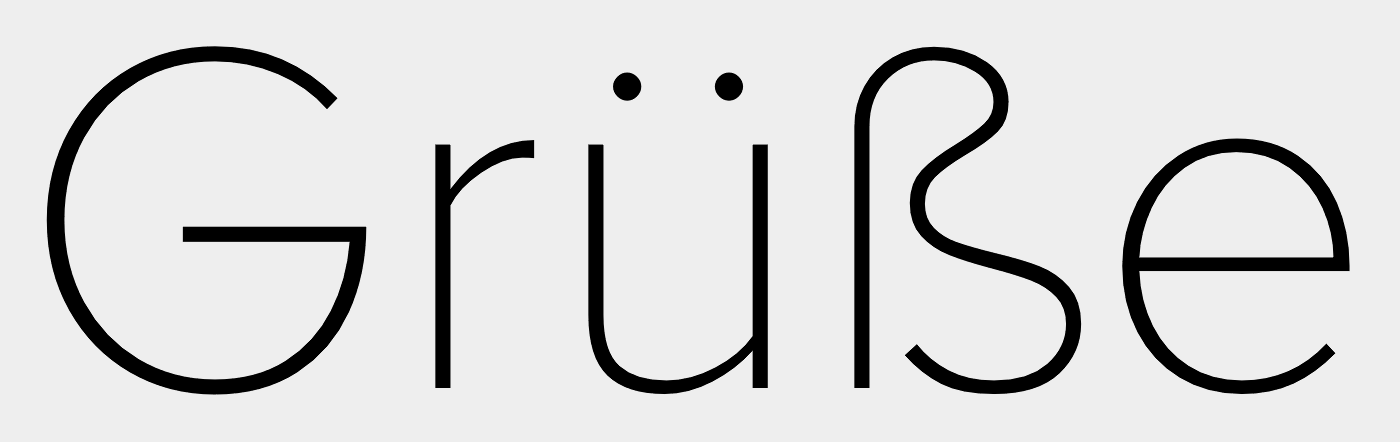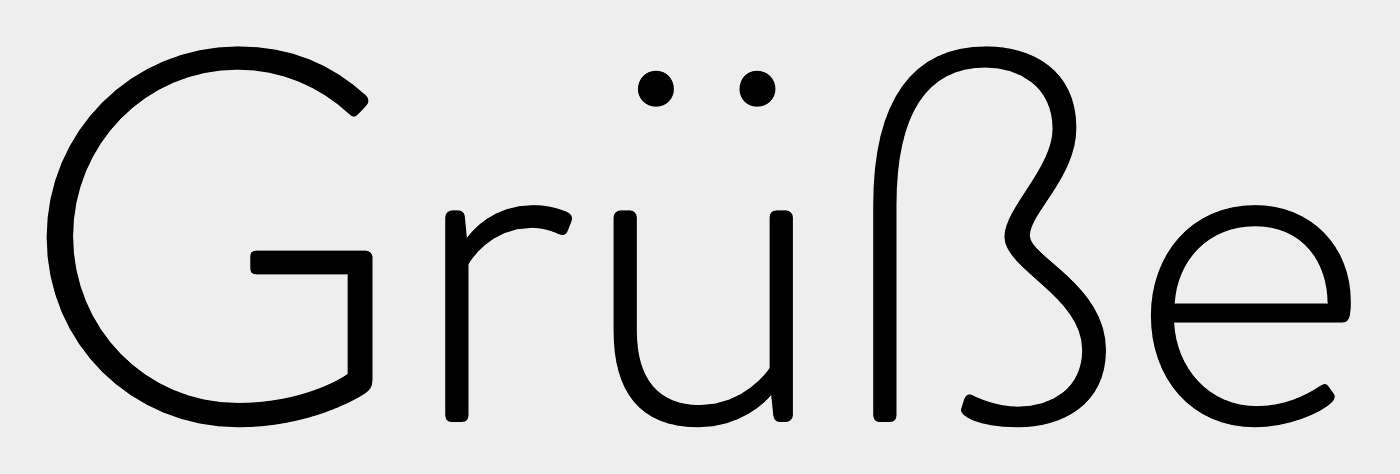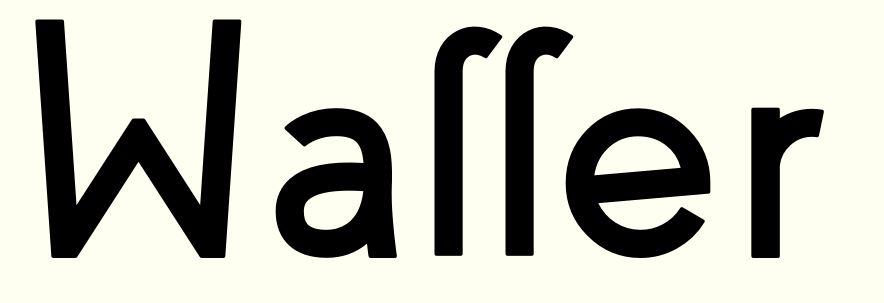
ß bei Schrift Coves
Wir gestalten Einladungskarten mit der Schrift Coves, die wir bei dafont bzw. befonts heruntergeladen haben.
Leider gibt es kein "ß" in dieser Schrift.
Hättet ihr mir einen Tipp, wie ich hier weiterkomme bzw. kennt ihr evtl. einen "erweiterten Schriftsatz" (wenn man das so nennen kann), bei dem das "ß" in der Schrift integriert ist?
Oder wißt ihr evtl. eine Schriftart, die der Coves nahe kommt und das "ß" keine Unterschied macht?
Ich wäre euch für eure Hilfe echt dankbar, da >anschliessend< oder >Grüsse< ohne "ß" einfach doof aussehen.
Wir gestalten Einladungskarten
Was ähnliche Schriften angeht, sag mal, was an der Coves es dir besonders angetan hat. Geometrische serifenlose Schmuckschriften gibt es nun wahrlich wie Sand am Meer. Und wenn es unbedingt kostenlose Schriften sein müssen, kuck lieber hier; diese Schriften dürfen auch kommerziell benutzt werden.
Oder wißt ihr evtl. eine Schriftart, die der Coves nahe kommt und das "ß" keine Unterschied macht?
Du willst das ß einer anderen Schrift mit Zeichen der Coves mischen? Vergiss das mal besser. Du könntest catfonts fragen, ob er dir ein passendes ß macht und wie viel Geld er dafür haben will.
Du hast nicht zufällig schonmal die Nachbarin mit deiner Mutter verwechselt?
Ja, das wäre der sinnvollere erste Schritt. Wobei die Wahrscheinlichkeit, dass du schneller als der Designer der Coves bist, recht groß ist.
Ich wäre euch für eure Hilfe echt dankbar, da >anschliessend< oder >Grüsse< ohne "ß" einfach doof aussehen.
Sag einfach, du hast die Karten exklusiv aus der Schweiz importiert :hammer:
Bei fontsquirrel sind doch ein paar Schriften, die als Ersatz passen, wenn dir das zu lange dauert, bis der Designer nachbessert. Warum gerade das ß fehlt verstehe ich auch nicht, sonst ist ja einiges dabei :-?
Vielen Dank für eure Tipps! Ich hab mal geschaut, von den Schriftvorschlägen lässt sich evtl. was verwenden....
Allerdings wärs halt schon ne runde Sache, wenn es das "ß" in der Schrift gäbe - ich habe es auch schon bei einem kommerziellen Papeteriehersteller gesehen:
Als Bild einfügen habe ich schon probiert, aber das ist auch icht das Gelbe vom Ei....
Ich bräuchte das "ß" halt demnächst... Ich frage auf ejden Fall mal bei dem Schriftdesigner Jack Harvatt an.
Es wäre aber wirklich toll, wenn catfonts mir helfen könnte!?!
Ich würde die Schrift wegpacken, wenn sie kein ß hat und komplett eine andere nehmen. Vielleicht bessert er irgendwann nach, dann kann man nochmal gucken. So ist sie für deutsche Texte unbrauchbar …
Wir sind auf die Schrift schon fetgelegt.... Wechseln geht nimmer... Einen Teil der Karten haben wir drucken lassen, einiges will ich jetzt noch selber machen...
Email a Jack Harvatt ist raus.
Aber falls mir hier jemand schneller weiterhelfen könnte, wäre ich dafür äußerst dankbar!
vor 1 Stunde schrieb toffie:
Ich hab mal geschaut, von den Schriftvorschlägen lässt sich evtl. was verwenden....
Das ist äußerst unwahrscheinlich. Die Zeichen in einer Schrift müssen sorgfältig aufeinander abgestimmt sein. Da kann man nicht einfach ein Zeichen aus einer anderen Schrift nehmen, ohne dass das auffällt. Es ist ja nicht nur die Grundform, die mit den anderen Zeichen harmonieren muss, sondern auch die durchschnittliche Strichbreite bzw. die wahrgenommene Strichbreite, der Wechsel der Strichbreite innerhalb der Zeichen, Kontrast u. s. w. Selbst Schriften, die auf den ersten Blick kontrastarm sind, sind meist nicht monolinear. Käme es nur auf die Grundform der Zeichen an, wären nicht hunderttausend oder mehr Fonts auf dem Markt. Typedesign gehört zu den anspruchsvollsten Aufgaben im Bereich Grafikdesign überhaupt, insbesondere das Design von Schriften, die für längere Texte bestimmt sind.
Der Begriff „Typeface“ deutet z. B. darauf hin, dass Schriften ähnlich gut unterscheidbar sind wie menschliche Gesichter. In eine Schrift einfach das ß aus einer anderen Schrift hineinzupacken, geht ebenso wenig, wie die Nase deiner Verlobten gegen eine beliebige andere auszutauschen.
Nebenbei: Ich frage mich, ob die Fähigkeit des Menschen, lesen lernen und Zeichen erkennen und auseinander halten zu können im Zusammenhang mit seiner Fähigkeit, Gesichter erkennen zu können, steht, ob also die komplexen sozialen Strukturen des Menschen, für die die Fähigkeit, die Mimik anderer Gruppenmitglieder einschätzen und die Gruppenmitglieder voneinander unterscheiden zu können,  unabdingbar ist, zur Entwicklung seiner Fähigkeit, lesen und schreiben lernen zu können, beigetragen hat.
Na, ich glaub, da kann ich mal ein Auge... ???
zumal:
Waſſer
Was? Ein ſ ist drin? Zufällig auch ein ʒ? Dann wäre das ß ja eigentlich auch naheʒu drin ...  Mit vielen Grüſʒen ...;-)